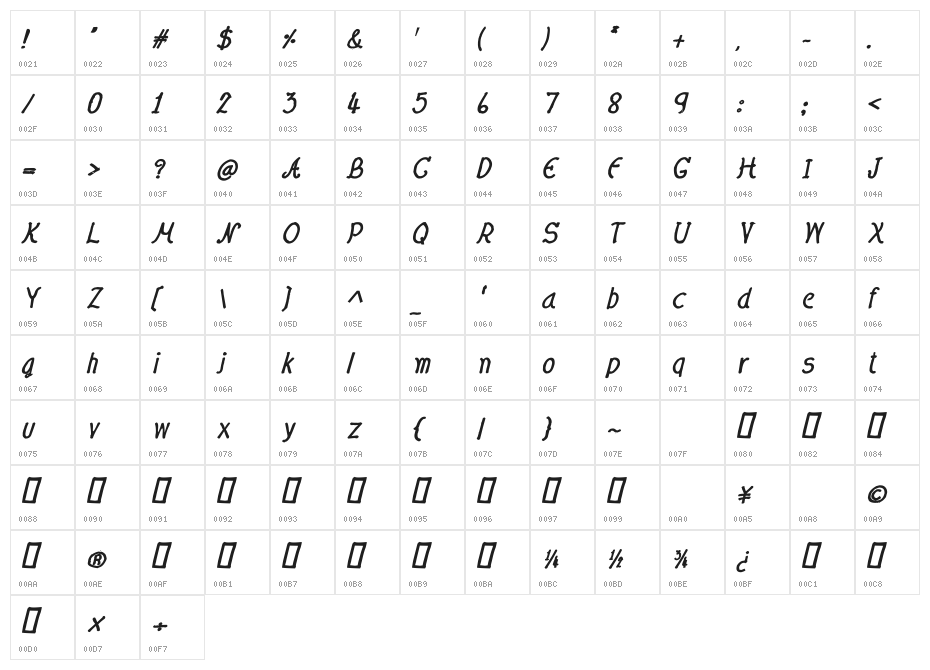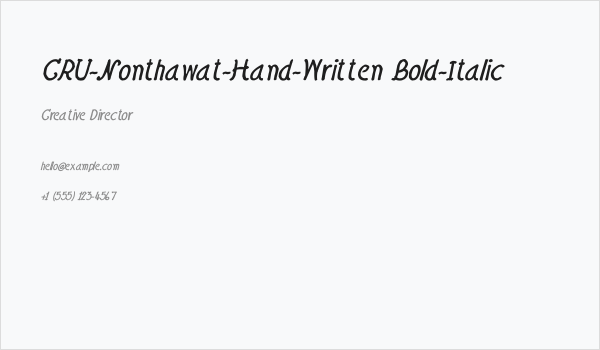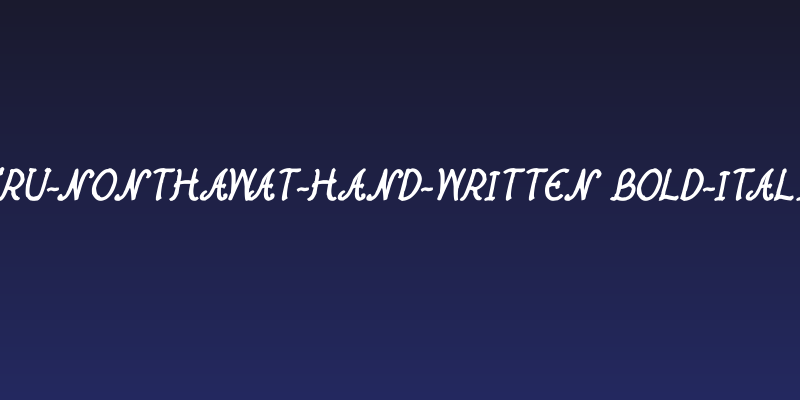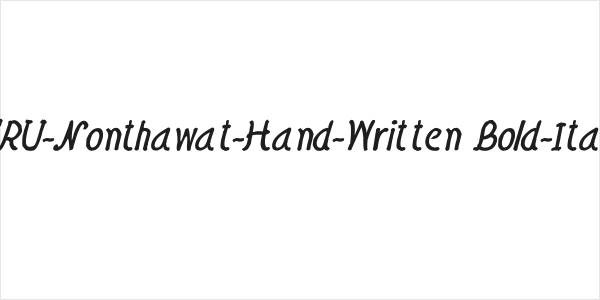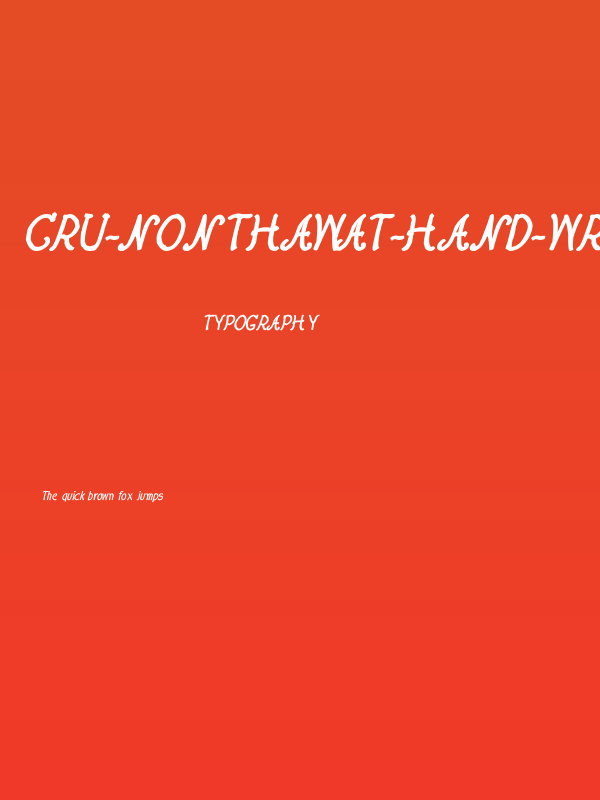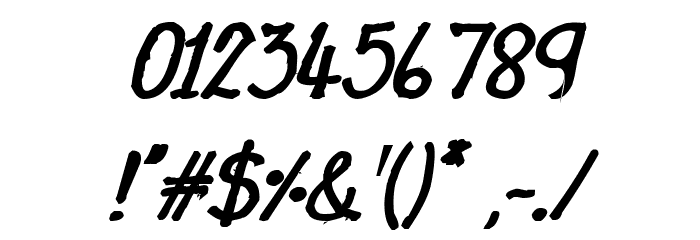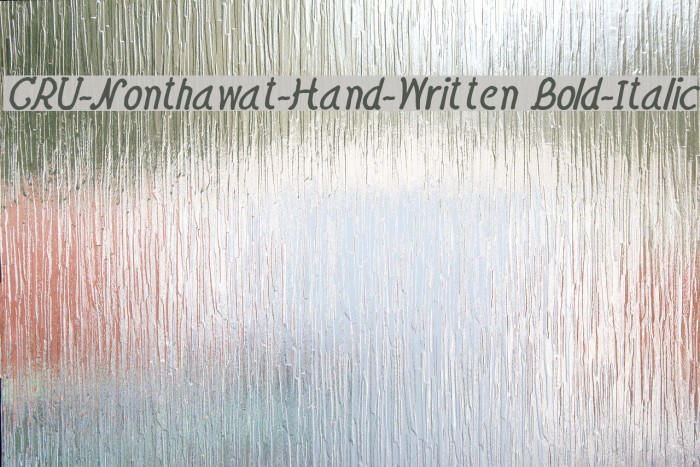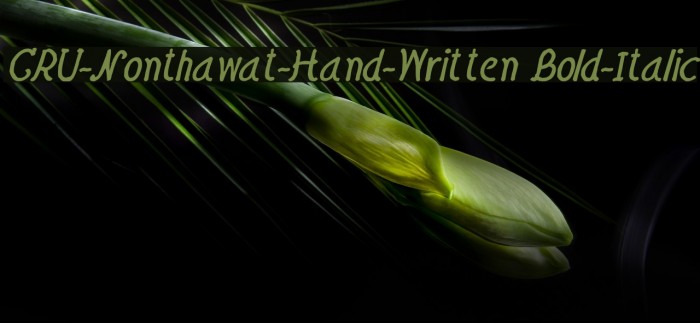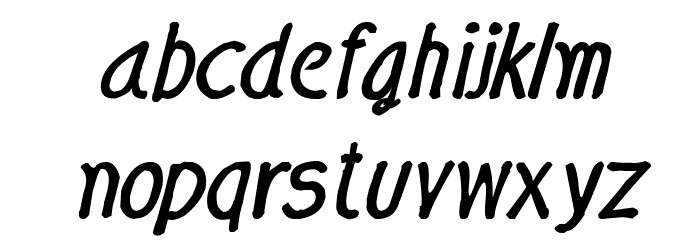
CRU-Nonthawat-Hand-Written Bold-Italic Font
| Cas d'utilisation | Logos, Headlines, Invitations |
| Projets proposés | Ideal for greeting cards, personal branding, invitations, and creative projects that require a personal touch. |